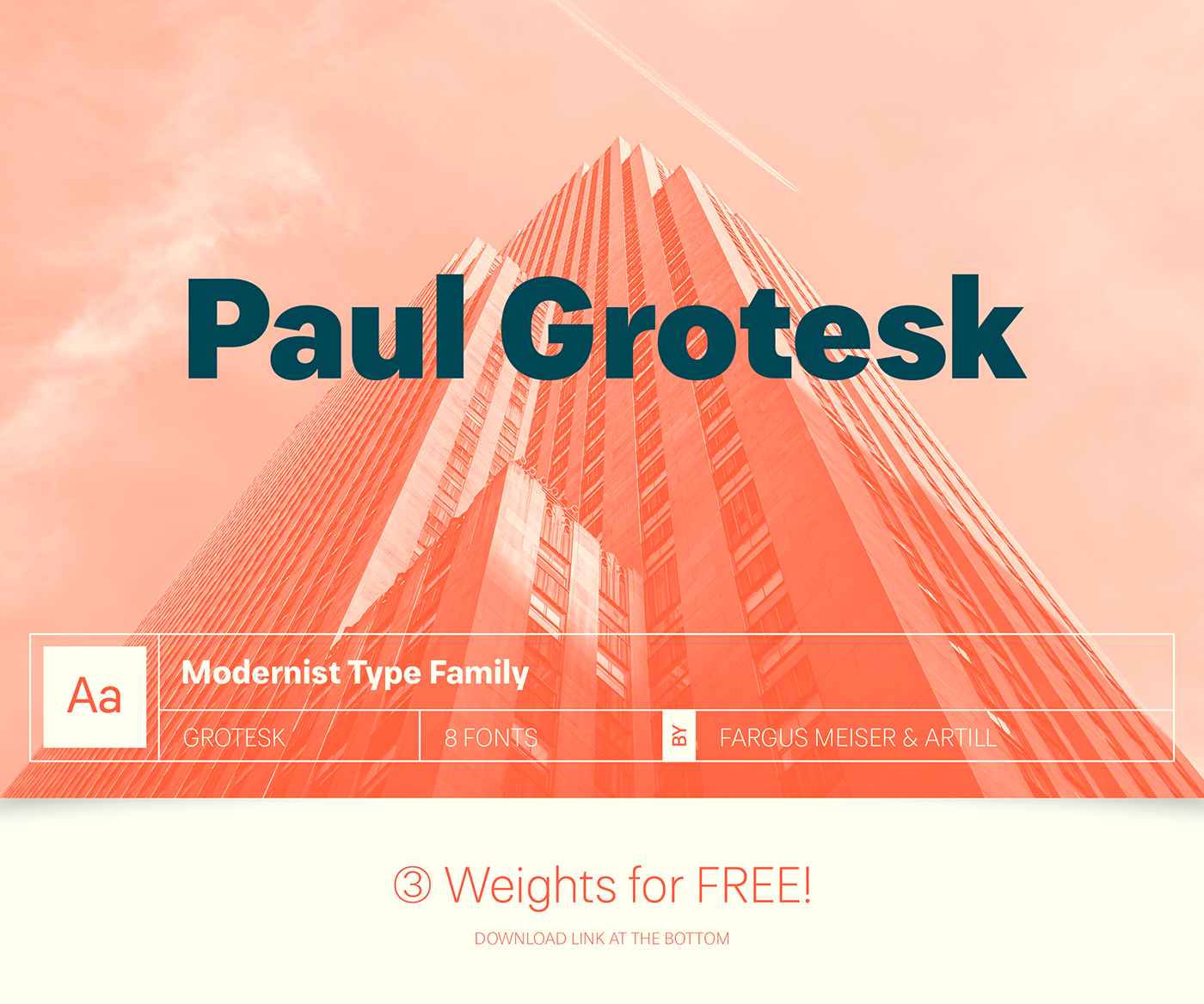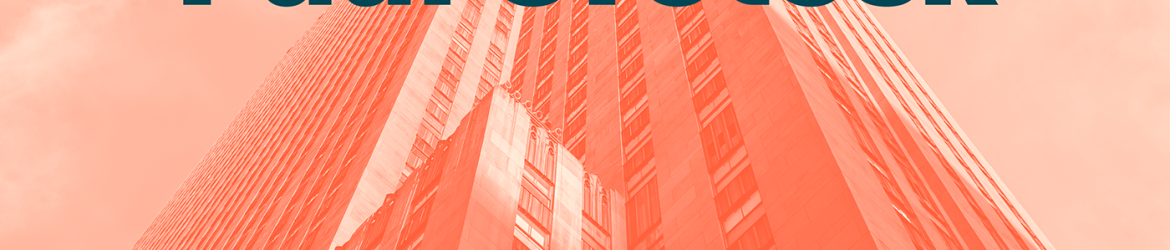
Introduzimos a Paul Grotesk para uma nova categoria de fontes modernas e poderosas. Esta sans-serif foi criada por Lukas Bischoff e agora pertence ao nosso catálogo. A Paul Grotesk é uma escolha ideal para designers que buscam um estilo clean e potente, com linhas finas e retas projetadas para dar uma sensação de leveza e modernidade a qualquer tipo de design gráfico. A Hamilton nos trouxe mais uma adição à nossa coleção de fontes sans-serif. A Paul Grotesk é um exemplo perfeito de como essas fontes podem transformar sua identidade visual, oferecendo um contraste elegante entre linhas suaves e formas geométricas. Suavizar a forma angular tradicional das serifas dá ao texto uma dinâmica leve que contrasta com os detalhes finos e bem projetados da Paul Grotesk. Com a Paul Grotesk, designers podem criar layouts contemporâneos sem perder o equilíbrio estético que tanto valorizam. Suavizar as linhas tradicionais das serifas criou um design de fonte com uma presença forte mas não dominante, adequado para textos em página ou mídias digitais. Talvez seja a Paul Grotesk a fonte perfeita para seu próximo projeto que busca um equilíbrio entre modernidade e elegância. Este é um produto da Hamilton que vale a pena explorar em sua coleção de fontes, trazendo uma experiência visual única para qualquer design de texto ou layout.